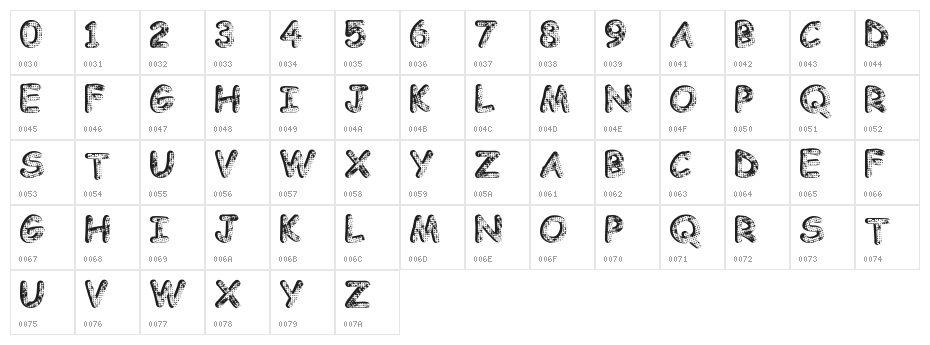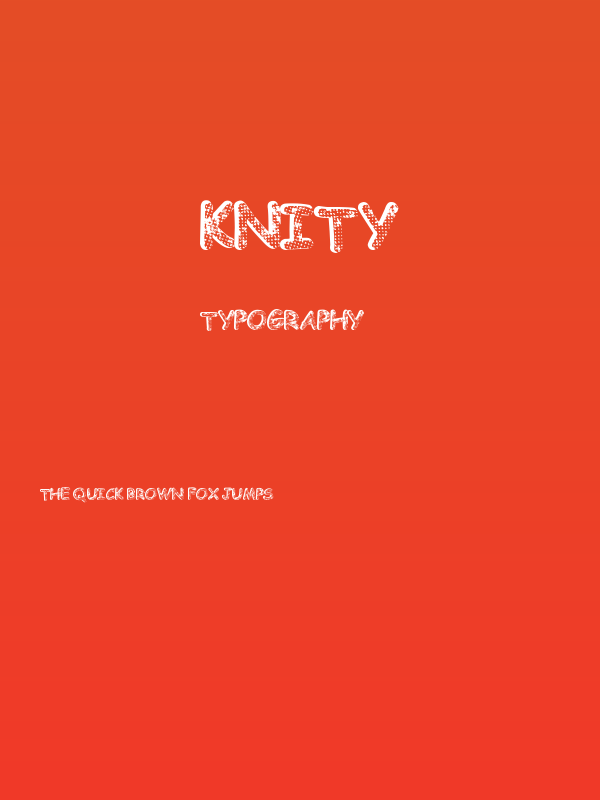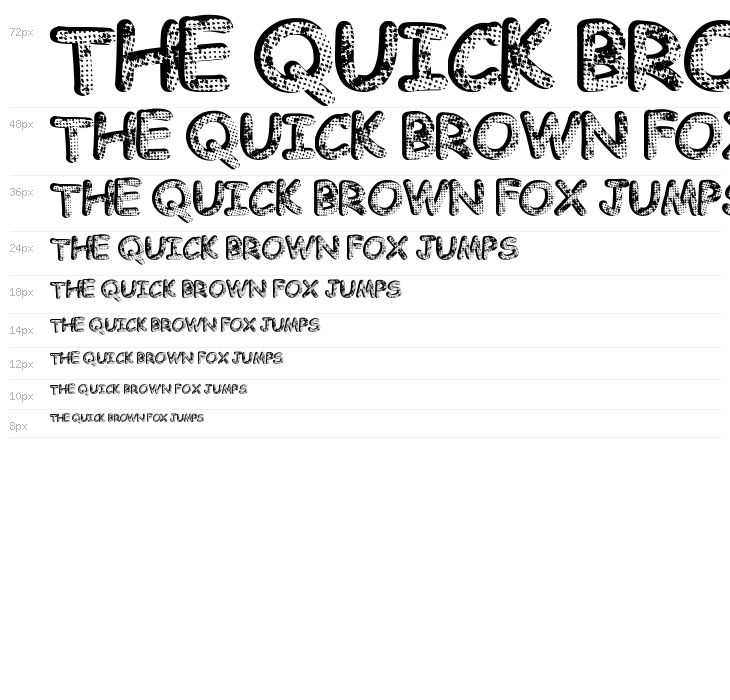
Knity Font
✎ Distorted Eroded
| Gesamtstil | Playful, Handcrafted |
| Vorgeschlagene Projekte | Ideal for crafting projects, children's books, playful branding, greeting cards, and DIY-themed designs. |